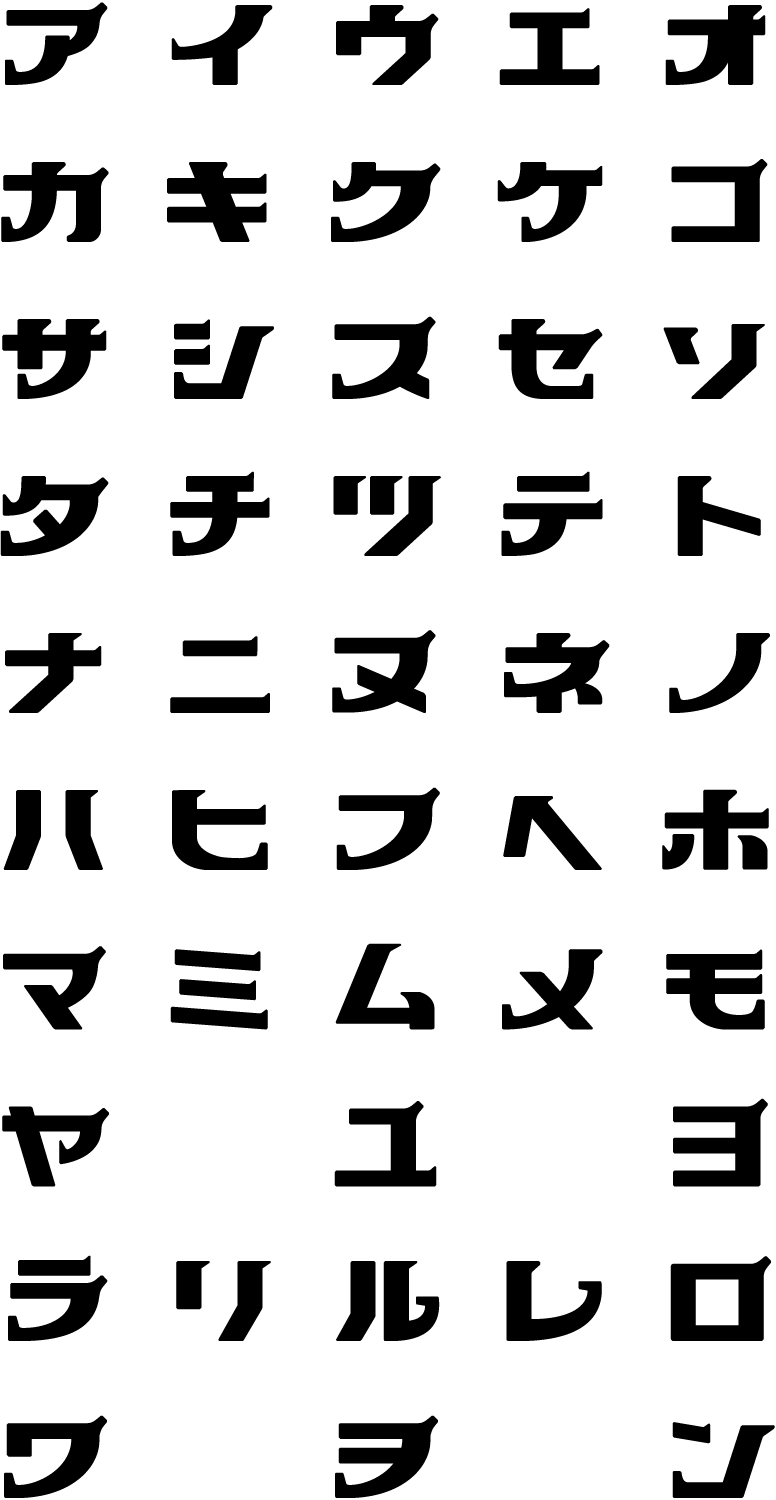
力強いフォルムの中に、さり気ない可愛らしさが。マッチョなのにキュート。難しい組み合わせを形にした書体である。
“Bandai Sports” was founded in 1956. Originally, they manufactured all kinds of nets for sports, and at that time, they were handmade with the help of craftsmen who made fishing nets for such as Omori Beach and Kujukuri-Hama Beach. Then, they turned to the current sporting goods store. They named the store Bandai Sports from the Bandai Bridge over the Shinano River, which did not collapse during the Niigata earthquake. “This typeface? I’ve been told for some time that it is an unusual typeface. We thought it wouldn’t be interesting if it were just a standard typeface, so we asked a designer to create it for our shop. It was rare for a sports shop to create such an elaborate typeface. For some reason, we had that kind of feeling back then.” Seiichi Kasahara and Osamu Kasahara, who runs the store, said. They also design uniforms and numbers themselves when they receive orders.